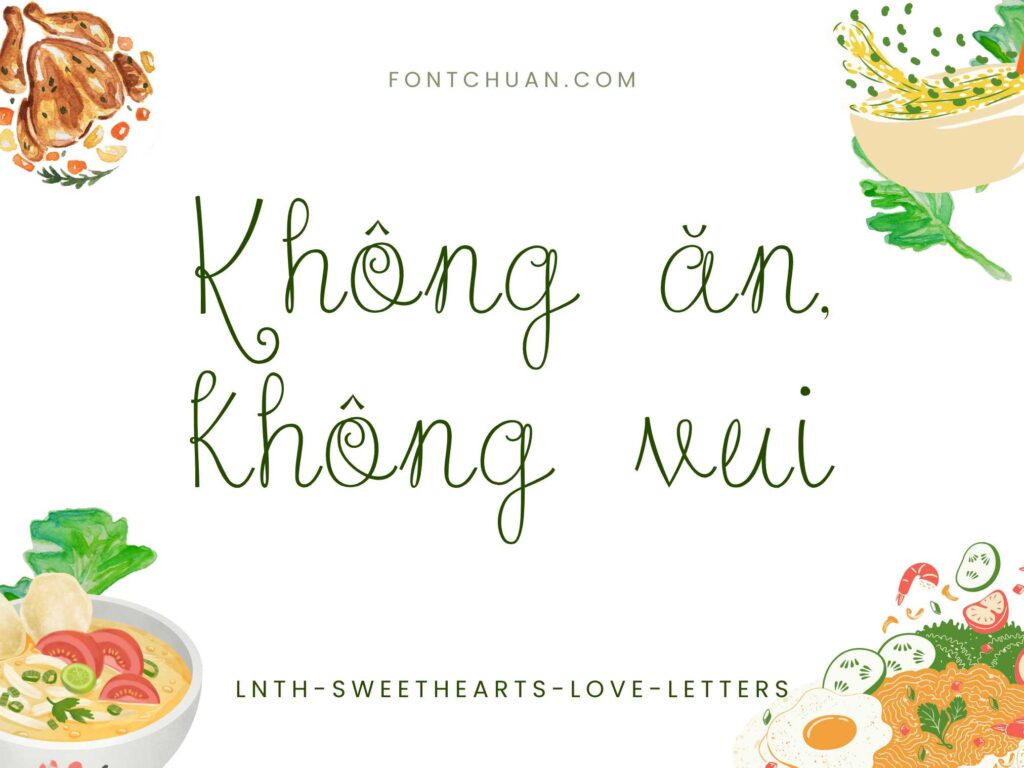
Font LNTH Sweethearts Love Letters Việt Hóa
Font Sweethearts Love Letters là một font chữ viết tay mềm mại, mang phong cách lãng mạn và bay bổng. Được thiết kế với các đường nét uyển chuyển và thanh thoát, font này thể hiện sự dịu dàng và tinh tế, rất phù hợp với các thiết kế về tình yêu, Valentine hoặc thiệp cưới. Sự mềm mại trong từng nét chữ giúp Sweethearts Love Letters trở thành lựa chọn hoàn hảo cho những ai muốn tạo ra những thiết kế mang cảm xúc đặc biệt
Phiên bản này đã được Việt hóa bởi LNTH, hỗ trợ đầy đủ tiếng Việt cùng hơn 50 ngôn ngữ khác, giúp người dùng dễ dàng ứng dụng trong thiết kế quốc tế. Font Sweethearts Love Letters được các thành viên Font Chuẩn sưu tầm và đăng tải nhằm đáp ứng nhu cầu tìm kiếm một kiểu chữ mang phong cách thư pháp lãng mạn, thích hợp cho các dự án sáng tạo mang chủ đề tình yêu và cảm xúc
Về đặc điểm thiết kế, Sweethearts Love Letters có các nét chữ uốn lượn mềm mại, độ dày mỏng linh hoạt, giúp tạo ra sự nhẹ nhàng và tự nhiên. Kiểu chữ này đặc biệt thích hợp để sử dụng trong typography nghệ thuật, thư mời, thiệp cưới, thiết kế logo, bao bì sản phẩm cao cấp hoặc các sản phẩm handmade
Font Sweethearts Love Letters được ứng dụng rộng rãi trong các sự kiện như Valentine, Thiệp cưới hoặc các dự án mang phong cách lãng mạn. Nó phù hợp với nhiều ngành nghề như quảng cáo, spa, ẩm thực, thiệp cưới